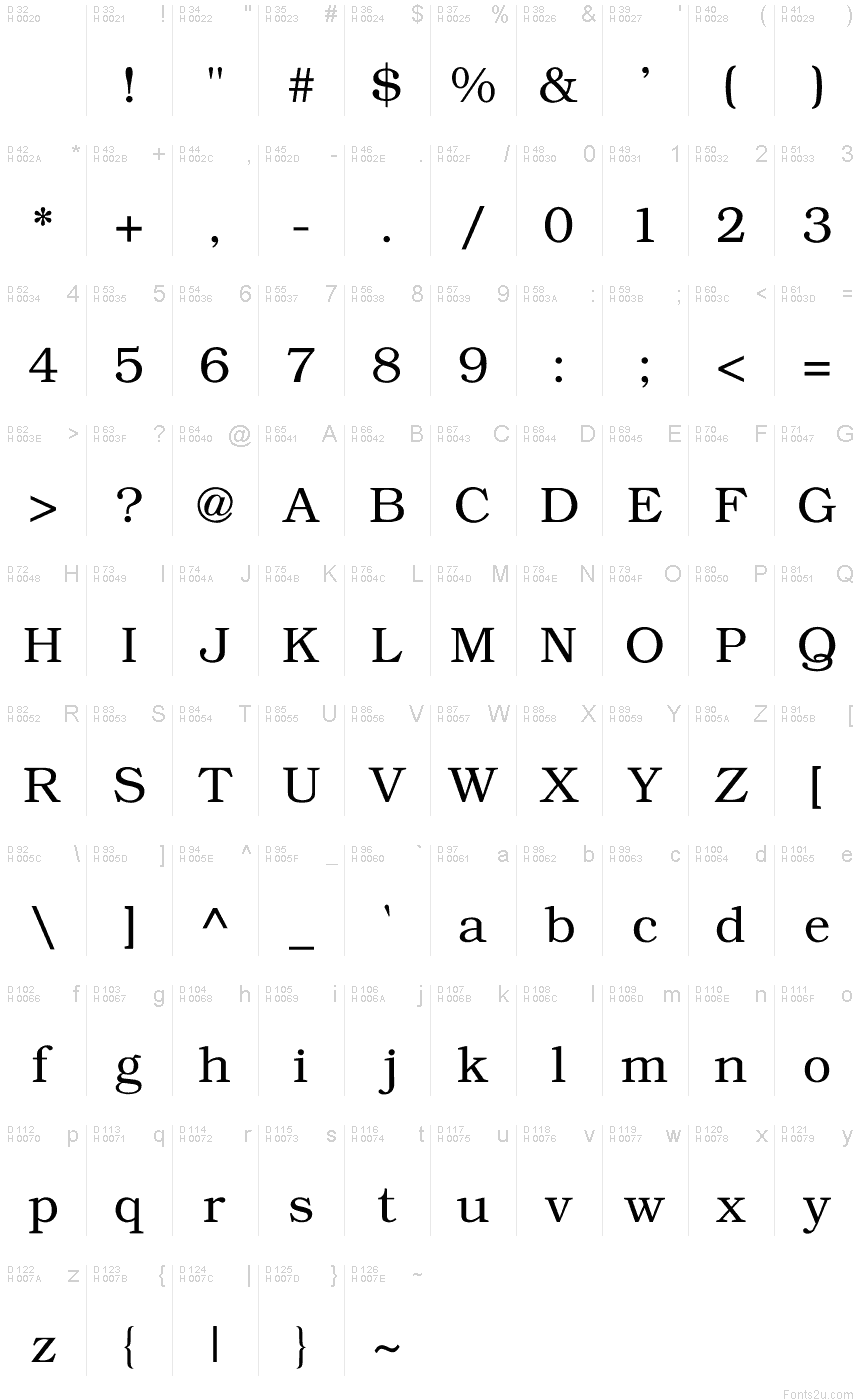
يُعد خط Angleterre Book من Digital Graphic Labs خطاً مجانياً من عائلة Angleterre، ويتميز بكونه مصمماً خصيصاً للقراءة الطويلة. حروفه رصينة وكلاسيكية، ذات ضربات دائرية ناعمة وتباين متوازن يضفي حيوية على الأسطر دون تشتيت الانتباه. تتمتع المسافات بين الحروف بطابع هادئ ومريح، مما يجعل الفقرات تظهر على الصفحة كأنها سطور في كتاب مطبوع كلاسيكي، بعيداً عن مظهر العناوين الرقمية البارزة.
باستخدام Angleterre Book، ستحصل على تجربة قراءة مثالية للروايات والمقالات والتقارير والمجلات والمنشورات الأكاديمية. يعمل هذا الخط المجاني بشكل رائع أيضاً في بدايات الفصول والمدونات الأدبية وملفات PDF المخصصة للطباعة، حيث تبرز الحاجة إلى نبرة هادئة وواثقة. جرب استخدامه مع خط بسيط بلا زوائد (Sans Serif) للعناوين وتسميات الواجهات، واضبط حجم Angleterre Book في النص الأساسي ليكون أكبر قليلاً من المعتاد لإبراز إيقاعه الأنيق.